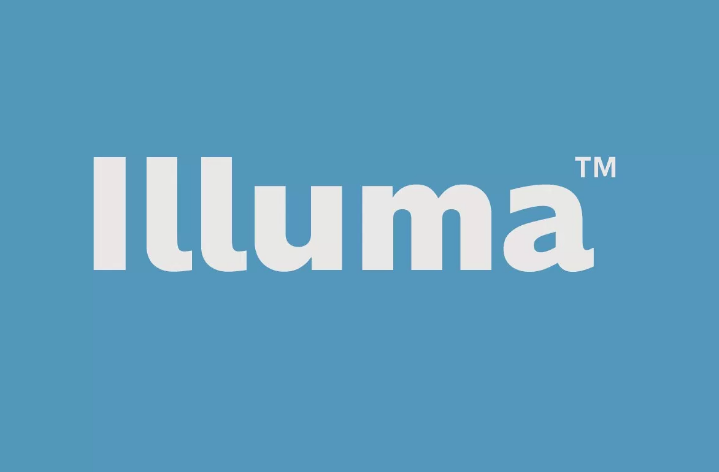
Illuma Typeface – Fonte Grátis
Illuma Typeface
Através do trabalho do designer Hamilton, a Imluma Typeface é uma sans serif que oferece impacto alto para aplicações de exibição como headlines e logotipos. Inspirado na simplicidade da iluminação, esta fonte atinge um nível superior de clareza e elegância. Ideal tanto para ambientes digitais quanto impressos, a Imluma está projetada para complementar uma variedade de projetos, desde editoriais até embalagens de produtos, marca ou materiais de ponto de venda. Com seu design clean e minimalista, a Imluma se destaca não apenas pela beleza visual, mas também por sua versatilidade. Suas linhas retas e claramente definidas permitem uma legibilidade excepcional em qualquer tamanho, tornando-a perfeita para headlines de grande impacto ou detalhes finos nas marcas. Seja no ambiente digital, na web ou em impressão, a Imluma é um recurso valioso para quem busca qualidade e estética.